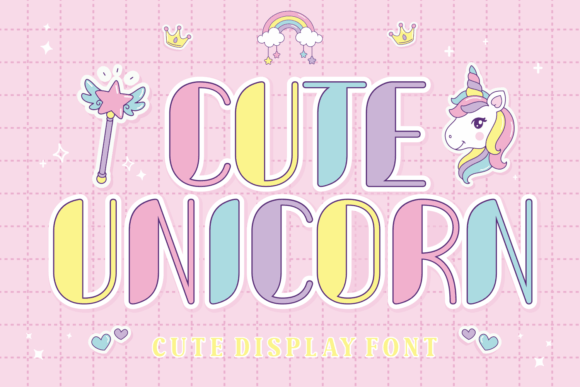
Cute Unicorn
Jika anda sedang mencari aset berkualiti tinggi seperti Cute Unicorn, pakej premium ini merupakan pilihan yang hebat untuk projek kreatif anda.
Sama ada anda mencipta produk POD (Print on Demand), jemputan perkahwinan atau grafik media sosial, Cute Unicorn amat bersesuaian.